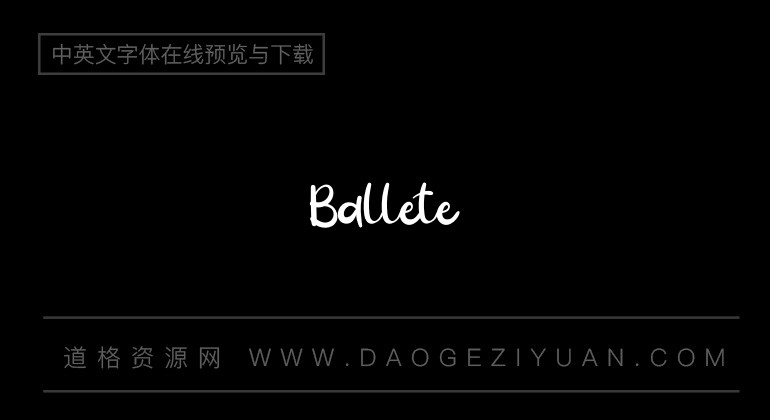
Ballete 字体是一款优美而优雅的手写风格字体,是由设计师 Alejo Bergmann 和制作人 Guille Vizzari 制作的。这款字体的设计灵感来自于芭蕾舞的优美和优雅,因此命名为 Ballete。 Ballete 字体具有精美的笔画和流畅的线条,适用于多种设计场景,如卡片、海报、标语、书籍封面等。Ballete 字体的特点在于它既有质感和厚度,又有一定的细致程度和流畅性,适用于多种文本排版。 Ballete 字体有多种字重和风格可供选择,包括常规、粗体、斜体、粗斜体等,能够满足不同排版需求。这款字体适用于许多语言,包括英语、西班牙语、法语、德语、意大利语、葡萄牙语等。 总的来说,Ballete 字体是一款优美且实用的字体,适用于多种设计场景,是设计师们非常喜欢的一款字体。内容介绍
Ballete是一款非常不错的手写艺术字体,具有很好的视觉感,适合于文化类的宣传设计、商业类品牌的广告和产品包装设计以及个性化文字排版等较多场景。